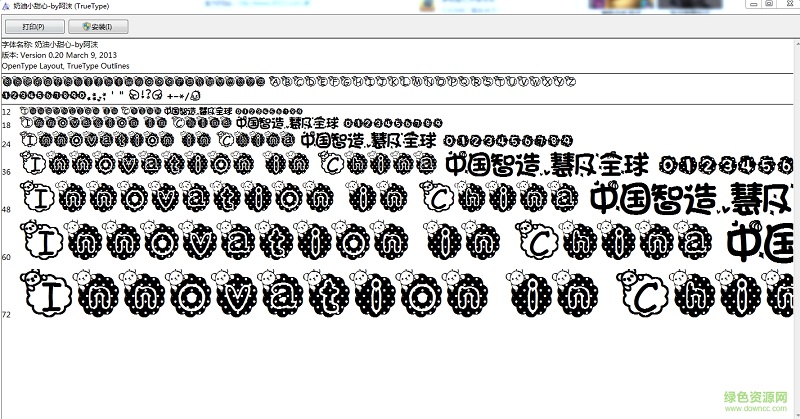
奶油小甜心字體是一款特別的阿沫字體,融合了小熊、餅干、圈圈等元素,字體形象新穎可愛,充滿童趣,可應(yīng)用于甜品、美食或兒童主題的設(shè)計方面,需要的朋友趕緊下載吧!
奶油小甜心字體是由阿沫設(shè)計的一款非常特殊的中文簡體漢字,擁有各種花紋裝飾、并且數(shù)字都帶有圓圈,但結(jié)構(gòu)清晰、風(fēng)格統(tǒng)一,能夠廣泛應(yīng)用于產(chǎn)品包裝、平面廣告、藝術(shù)創(chuàng)作、兒童設(shè)計等應(yīng)用!